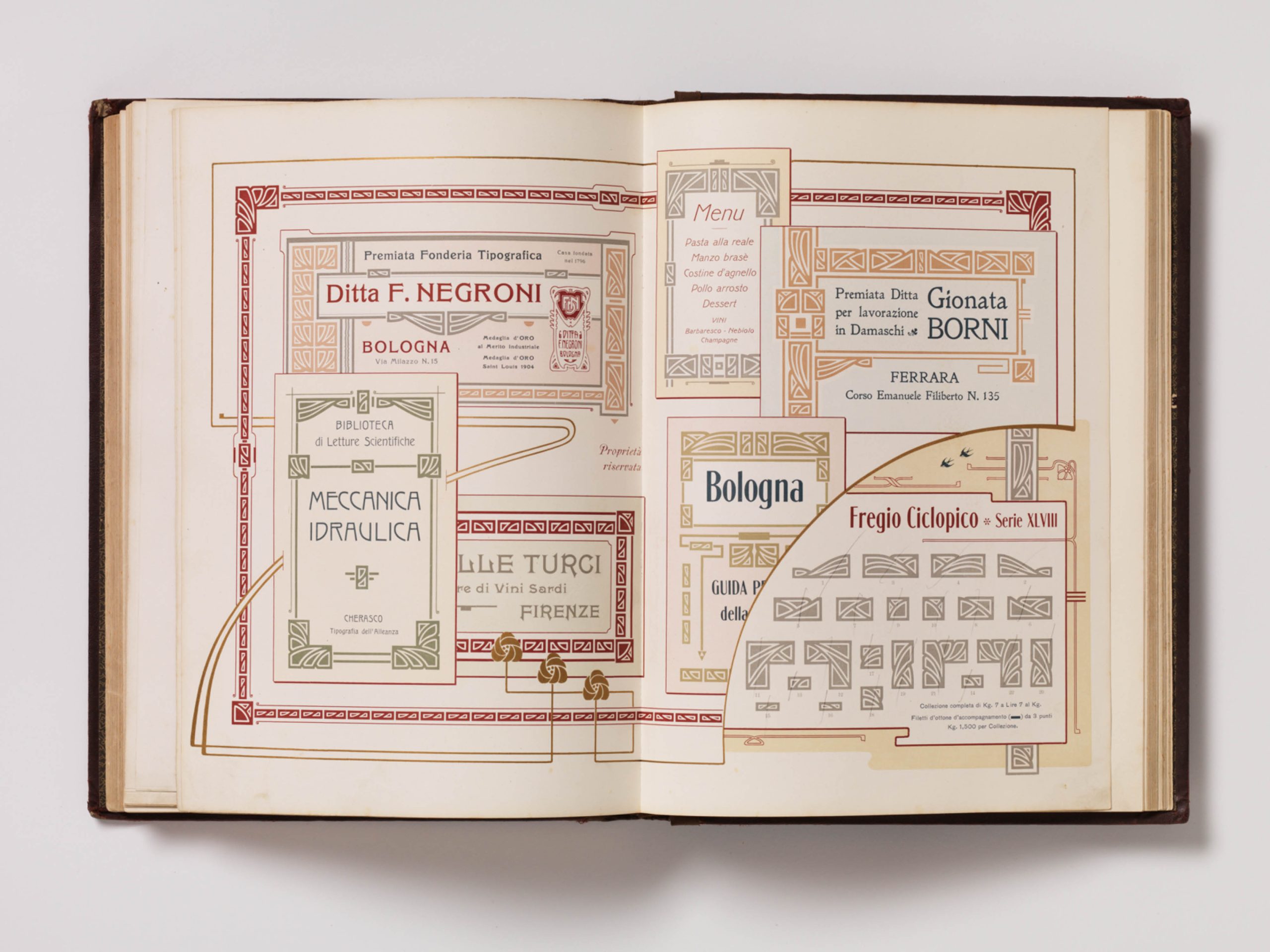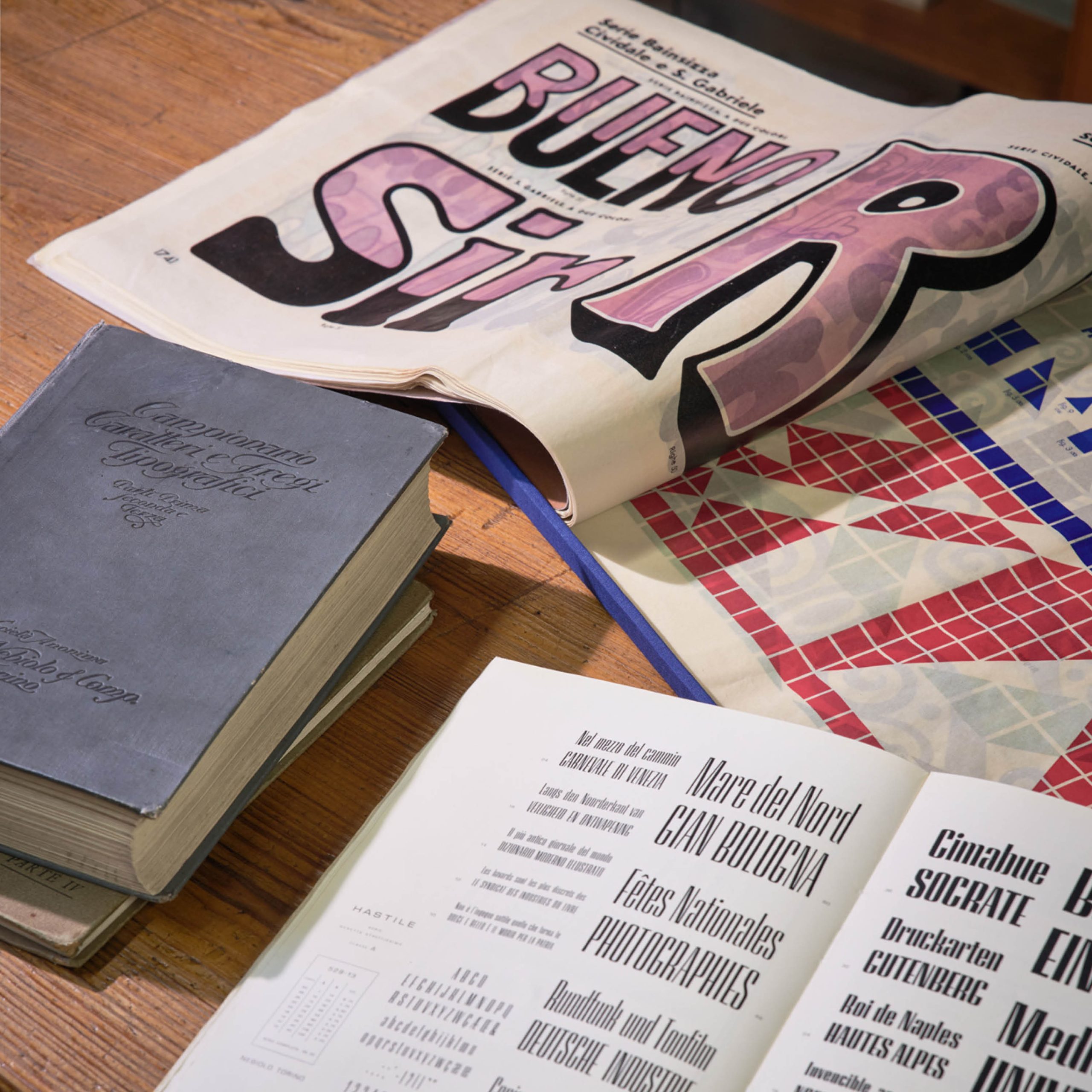
I campionari dei caratteri
La modernizzazione tecnica in ambito tipografico che ebbe inizio con la Rivoluzione Industriale coincise con l’evoluzione estetica dei caratteri: le Fonderie e in generale le aziende produttrici di tipi ebbero la necessità di rendere visibili le nuove introduzioni sul mercato, e iniziarono a stampare regolarmente dei Campionari di caratteri. Durante la visita hai già avuto modo di incontrare uno dei più mirabili esempi di Campionario, ovvero il Manuale Tipografico di Bodoni: in quel caso, si tratta soprattutto di uno straordinario esercizio di stile dal punto di vista estetico. Dalla fine dell’Ottocento si diffonde un tipo di stampato più pratico, utile ai tipografi per rimanere aggiornati sulle novità di una certa Fonderia e scegliere all’interno di una gamma di forme sempre più vasta: per questo motivo i caratteri venivano organizzati in base alla categoria. Esistono campionari per i caratteri in piombo e per i caratteri in legno. Nei primi, sono presenti dei testi in tutti i corpi (di solito dal corpo 6 al corpo 48 o 60) di un determinato stile e, in genere, un alfabeto completo; nei secondi, per ogni corpo si trova spesso solo una singola parola o un insieme di lettere, disposizione che non permette di avere una visione d’insieme dell’alfabeto.